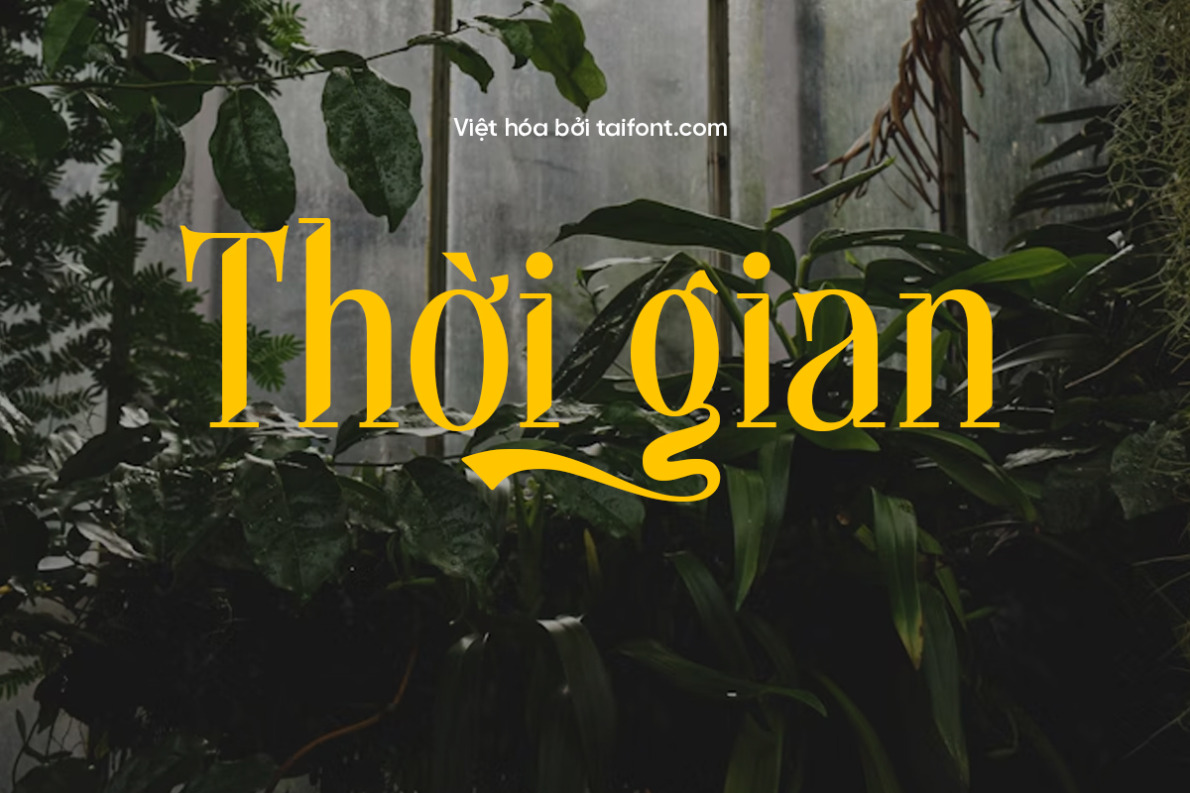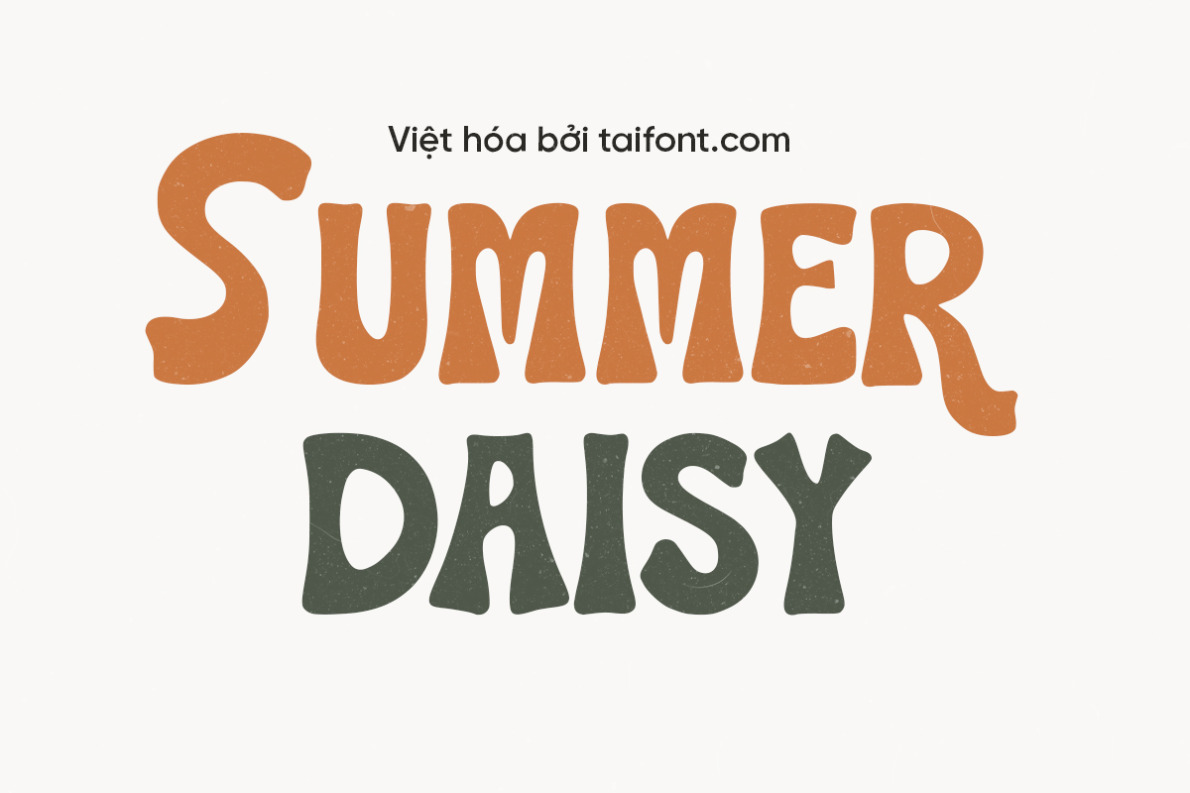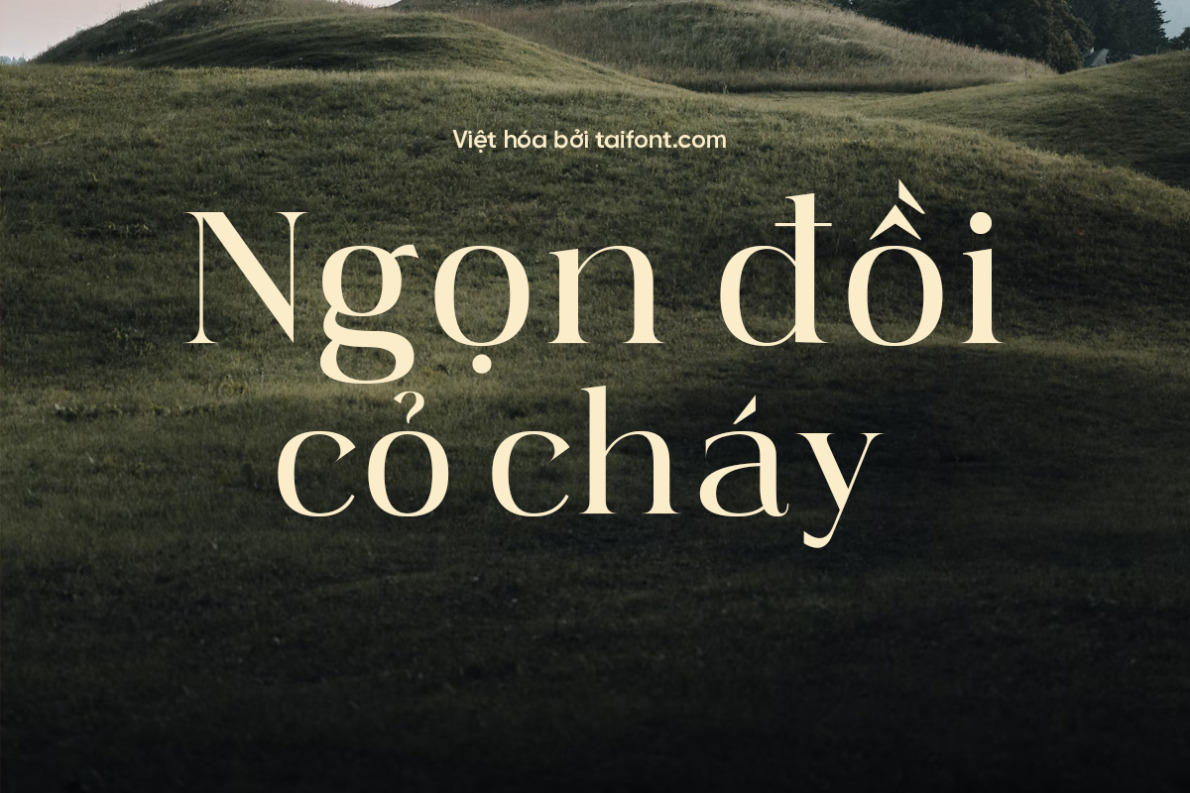
Một số font chữ tiêu biểu
Font Việt hóa TF Colette
TF Colette Việt hóa là một font chữ có chân (serif) nổi bật với thiết kế thanh lịch, tinh tế và đầy sang trọng. Font này mang đến vẻ đẹp cổ điển kết hợp hiện đại, toát lên phong thái quý phái, đẳng cấp và sự cuốn hút đặc biệt, lý tưởng cho mọi ấn phẩm cần sự tinh xảo và độc đáo.
Font Việt hóa TF Sabiant – Nhiều glyphs
TF Sabiant Việt hóa là một font chữ có chân (serif) nổi bật với vẻ đẹp sang trọng, tinh tế và đầy cuốn hút. Font này được thiết kế với những đường nét thanh lịch, mềm mại nhưng vẫn giữ được sự rõ ràng và chuyên nghiệp, toát lên phong thái quý phái và đẳng cấp, lý tưởng để tạo nên sự độc đáo cho mọi thiết kế.
Font Việt hóa TF Summer Dais
TF Summer Daisy Việt hóa là một font chữ nổi bật với thiết kế to lớn, đầy đặn và mang vẻ ngoài tươi vui, rạng rỡ, như một đóa hoa cúc mùa hè. Font này gợi cảm giác về sự hồn nhiên, sự thoải mái và đầy năng lượng tích cực, lý tưởng để thu hút sự chú ý và tạo không khí vui tươi, gần gũi.